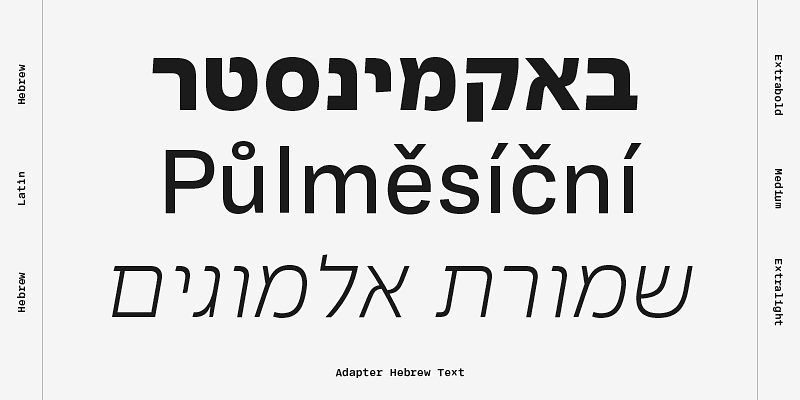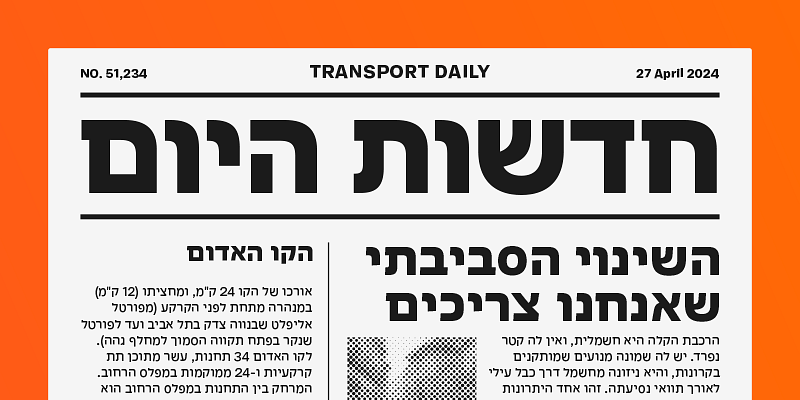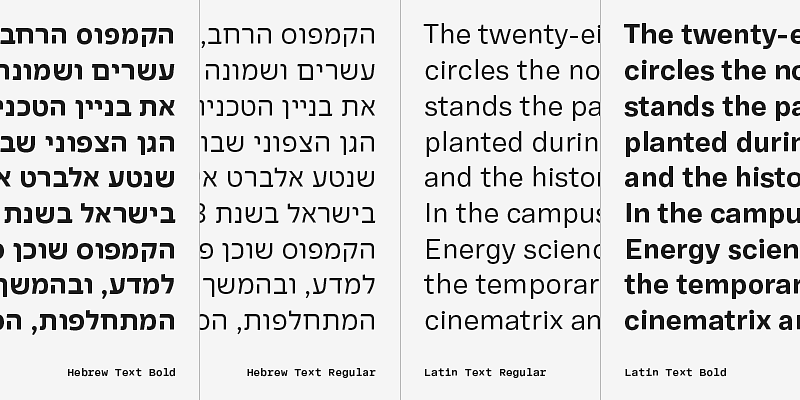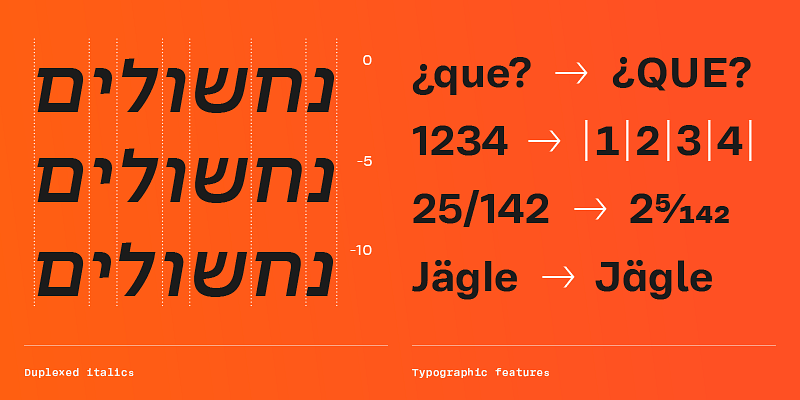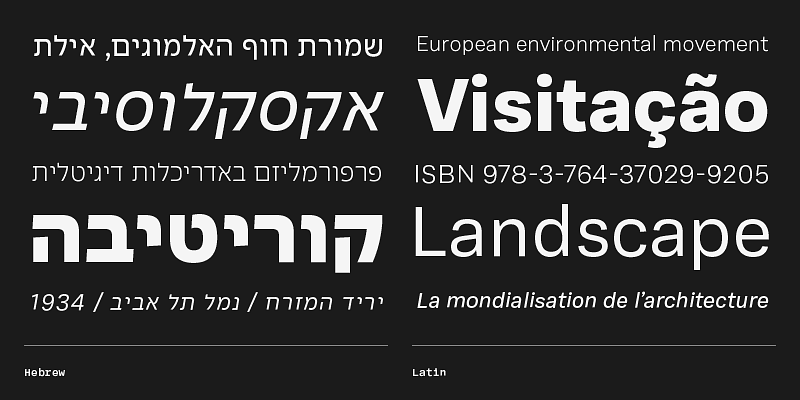
Police d’écriture monolinéaire universelle à l’esthétique contemporaine. Ses deux variantes par taille, Texte et Affichage, sont rassemblées dans un système typographique qui propose une large gamme de graisses et d’italiques à largeur unique dans une seule police variable.